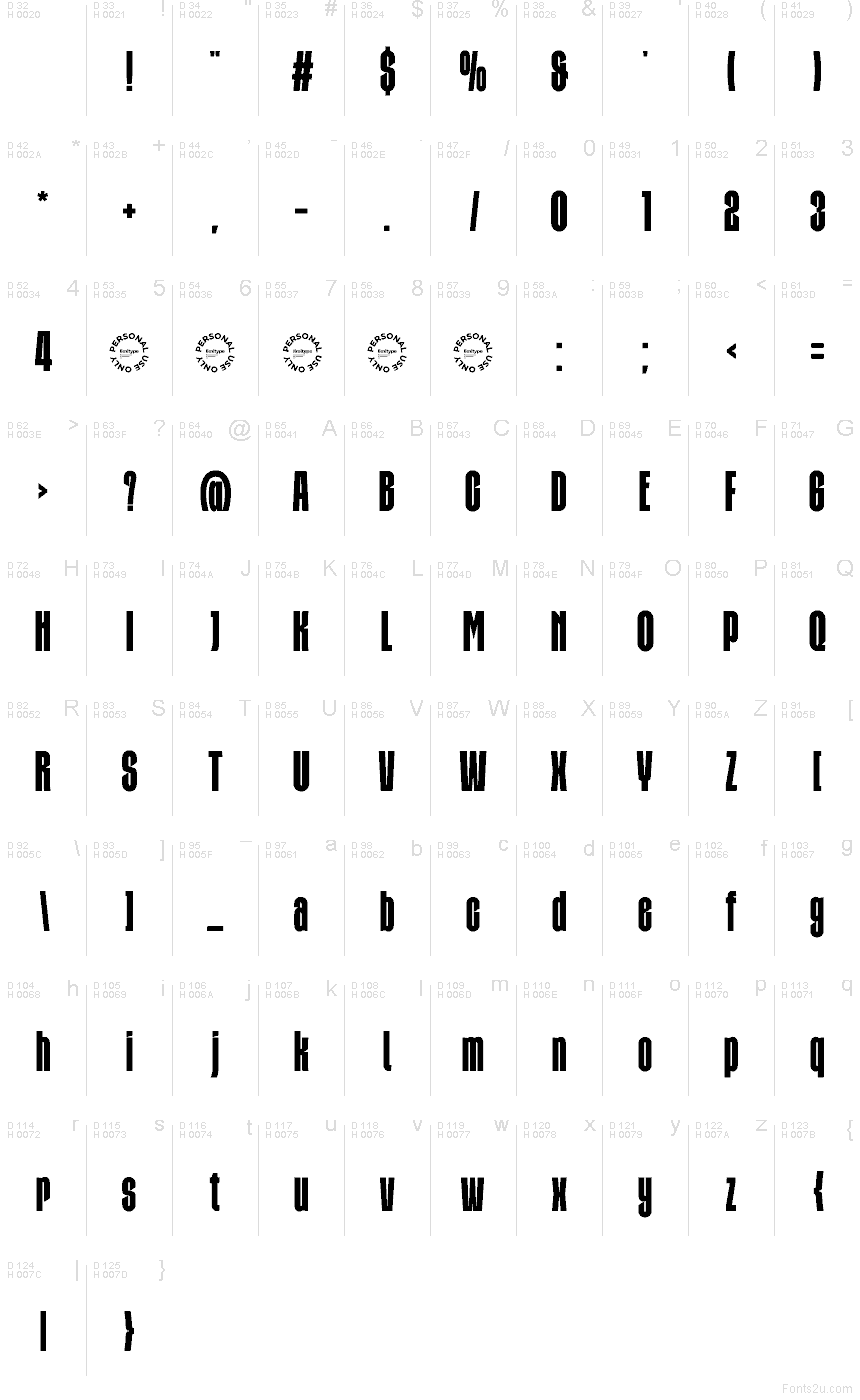
Daltown da Limitype é uma fonte display sem serifa condensada e gratuita, com uma estrutura marcante e ideal para cartazes. As suas letras altas e justapostas utilizam traços largos e formas truncadas, com curvas arredondadas que suavizam a silhueta densa.
Designers que trabalham com streetwear, desporto ou música acharão o seu impacto comprimido útil para merchandising e cartazes de eventos. Transforma um nome curto num bloco compacto. As mesmas formas robustas adequam-se a embalagens de alimentos e a títulos fortes de capas de revistas.